作为全球知名的字体科技公司,蒙纳字库将以其专业视角和创新技术,展示字体如何成为提升体验设计的重要力量。
在体验设计领域,字体缘何如此重要?
在体验设计领域,尤其是数字界面,每一个像素都意义非凡,然而字体发挥的作用却时常被低估。字体绝非仅仅是页面上的文字符号,它们是强大的交流工具,也是用户界面(UI)和用户体验(UX)不可或缺的元素。字体能够左右用户的满意度、文本的可读性与易认性,甚至能决定一款数字产品的成功与失败。
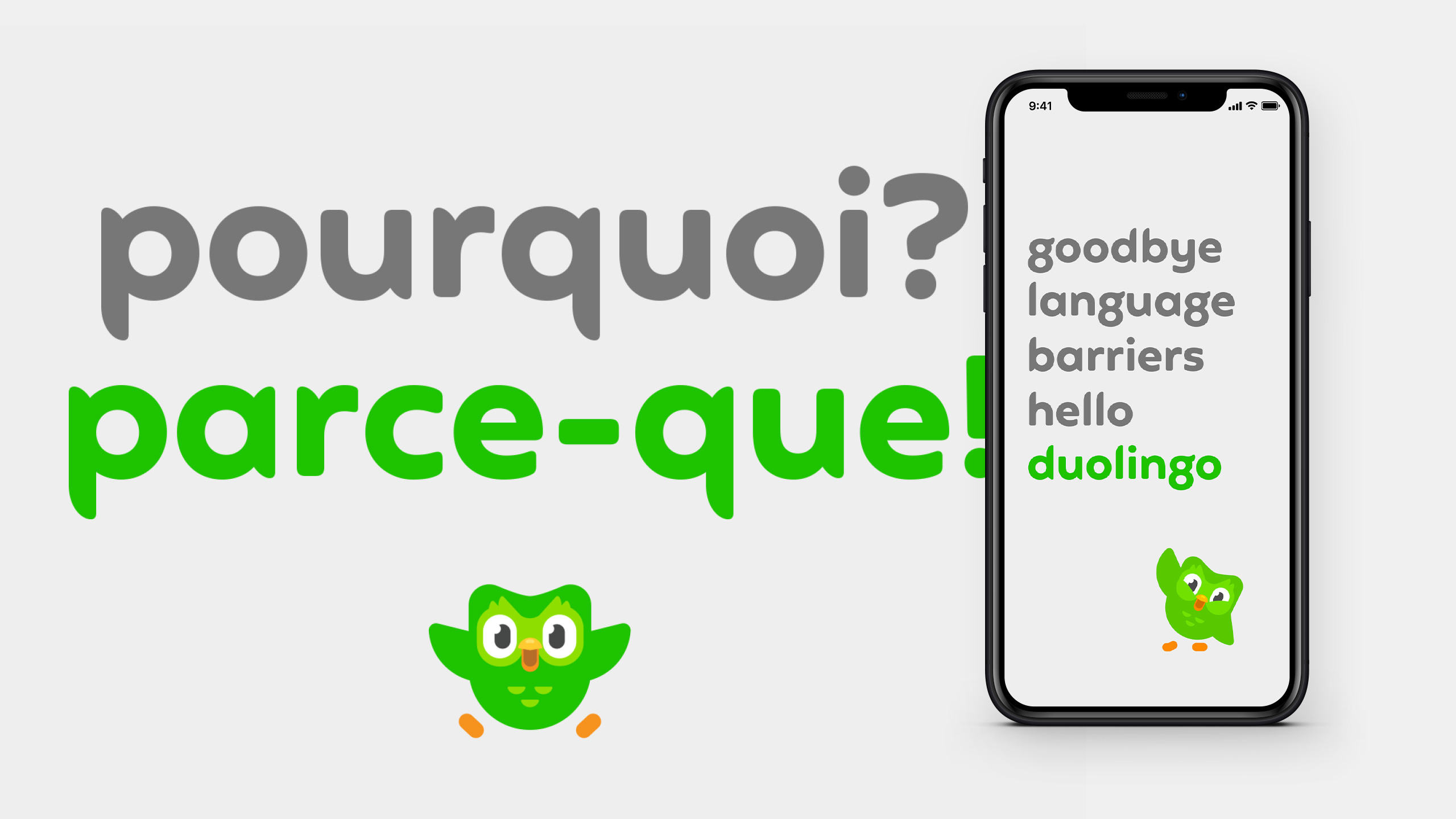
● 可读性与清晰度
在体验设计当中,字体的首要功能在于轻松传递信息。优质的字体能够增强可读性,确保用户可以快速汲取内容。清晰的字体能够规避理解偏差,这在说明性或者数据密集型的内容里显得尤为关键。
● 层次结构与视觉引导
借由改变字体的粗细、大小以及样式,我们能够构建清晰的视觉层次,引导用户浏览界面,凸显重要的信息或者行动召唤。
● 品牌形象
字体是品牌形象的关键构成部分。它们传递着品牌的声韵和个性,塑造出令人过目不忘且连贯统一的品牌体验。字体能够传达出信任、喜悦、精致或者创意等意象,成为品牌实现差异化的重要手段。不同的字体能够唤起各异的情感。精心拣选的字体能够影响界面的基调,不管是活泼的氛围,还是专业的感觉,字体都能够传递对应的情感反馈。
● 美学吸引力
美学在用户的参与感方面扮演着至关重要的角色。相较于平淡乏味的界面,一个富有设计感的界面更易于留住用户。字体让视觉更加和谐,强化布局与结构,进而提升用户的满意度。
● 无障碍性
挑选适宜的字体能够提升设计的无障碍性,使得视障人士也能够加以使用。某些字体专为提高可及性(Accessiblity)而设计,支持更优质的交互与包容性。
蒙纳字库 Monotype Fonts 助力提升体验设计?
Monotype Fonts 是一个全方位的平台,旨在满足设计师、品牌以及组织的多元化设计需求。平台整合了强大的工具和资源,帮助企业在数字和印刷项目里有效地管理、挑选以及应用字体。
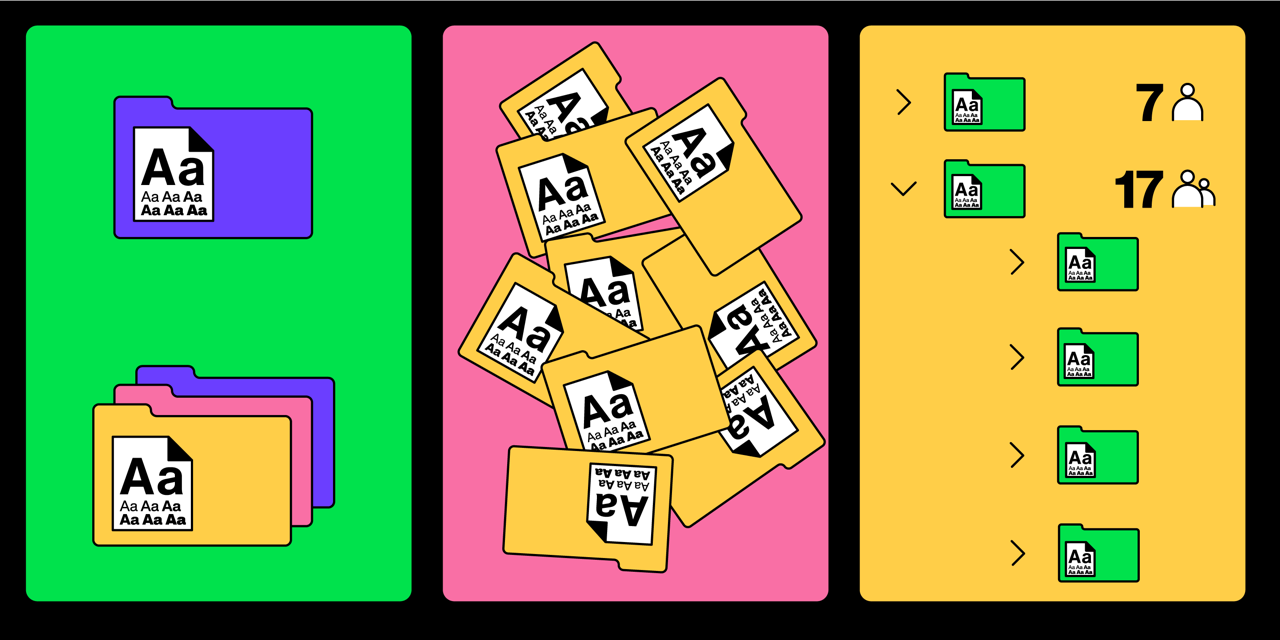
● 丰富的字体库
Monotype Fonts 是一款规模庞大且种类多样的字体库。平台提供来自知名字体公司近 20 万款字体,让设计师面对任何项目都能找到完美适配的字体。
● 高级搜索和筛选
Monotype Fonts 拥有强大的搜索和筛选功能,用户可以依据样式、粗细、语言支持等维度检索挑选字体。比如,设计师想要获得一款适合儿童读物的字体,通过输入“可爱”“童趣”等关键词,快速找到符合要求的字体。
● 统一便捷的字体管理
平台简化了字体管理流程,让团队在一个集中的位置组织和管理字体合集。这保障了项目之间的一致性,并且让与团队成员的协作更为便捷。
● 与设计工具集成
Monotype Fonts 与流行的设计软件(如 Adobe Creative Cloud)实现了无缝集成,让设计师直接在偏好的设计环境中使用字体,简化工作流程。
● 支持和资源
平台提供了丰富的教育资源、教程以及专家支持。蒙纳的客户支持团队随时协助解答任何疑问。
Monotype Fonts 简化了查找、管理和使用字体的流程。借助 Monotype Fonts,设计师可以获得更多创意来源,确保品牌一致性,并在所有数字和印刷媒体中提供卓越的用户体验。